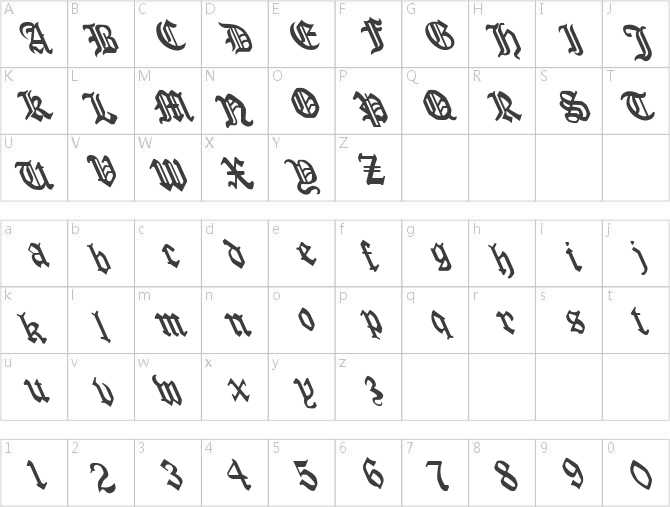
FZ GOTHIC 4 LEFTY 詳情頁
FZ GOTHIC 4 LEFTY字體字庫是一款讓人賞心悅目、百看不厭的英文字體,適合各類廣告和產(chǎn)品包裝設(shè)計(jì)應(yīng)用,字體大小0.05MB,格式為ttf字體,上傳用戶是眾聯(lián)齊成,作者/版權(quán)方為未知